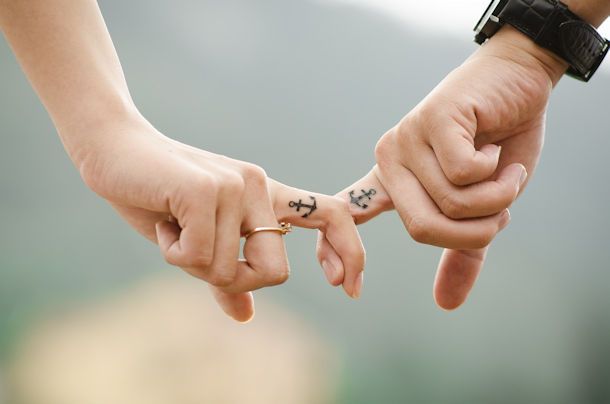
Migliori font per tatuaggi
Ci stavi pensando da tempo e adesso ti sei finalmente convinto a fare quel tatuaggio che desideravi tanto. Si tratta di una scritta, una frase o una parola che ti ricorda un momento speciale o rispecchia la tua personalità. Per questo hai deciso di metterti alla ricerca dei migliori font per tatuaggi, perché nulla va lasciato al caso. Deve essere tutto perfetto, carattere compreso: questo progetto ti sta particolarmente a cuore e vuoi ottenere il miglior risultato possibile.
Ti capisco, d'altronde il lato estetico di un tattoo non è affatto da sottovalutare. È giusto voler individuare lo stile di scrittura che meglio esprime il significato di ciò che stai per tatuare. E poi anche l'occhio vuole la sua parte, non è così? E allora nei prossimi paragrafi troverai tanti font tra cui scegliere, suddivisi per categoria, e non ci sarà soltanto il classico stile romano.
Non mi resta quindi che augurarti buona scelta, oltre a consigliarti di seguire le mie indicazioni per ottenere il font che preferisci o per spiegare al tuo tatuatore come realizzarlo. Sei pronto? Benissimo, anch'io lo sono: direi che possiamo iniziare a esplorare i numerosi caratteri che ho raccolto per il tuo prossimo tatuaggio. Buona lettura!
Come scegliere il font del tatuaggio
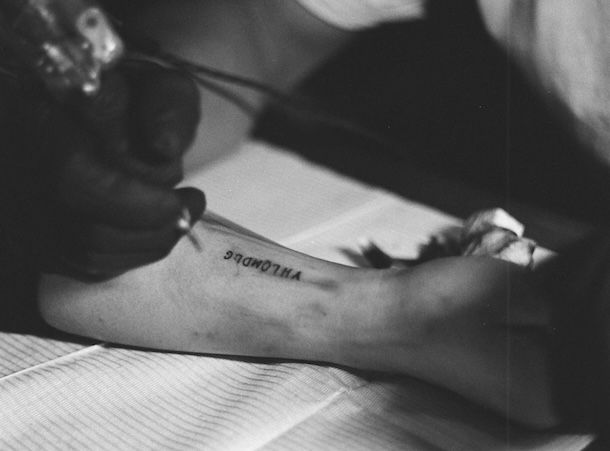
Il modo migliore per scegliere il font del tatuaggio è pensare al significato di ciò che stai per scrivere e all'effetto che desideri ottenere. Se, per esempio, vuoi trasmettere forza e decisione, potrebbe essere più adatto un carattere in stampatello maiuscolo, mentre se invece preferisci qualcosa di più elegante o romantico, i corsivi rappresentano spesso la soluzione ideale e ne esistono davvero di molto belli.
Nel caso in cui fossi totalmente indeciso, il mio consiglio per individuare i migliori font per tatuaggi è quello di selezionare diversi stili tra quelli che preferisci, installarli e provare a scrivere la parola o la frase del tattoo con ciascuno di essi. Guardando il risultato finale riuscirai più facilmente a capire quale tipologia di scrittura ti comunica le sensazioni che desideri evocare.
Tieni presente anche un altro aspetto importante: i caratteri troppo elaborati possono risultare difficili da leggere, soprattutto nei tatuaggi di piccole dimensioni. Per questo motivo è sempre bene trovare un giusto equilibrio tra estetica e leggibilità.
Migliori font per scritte tatuaggi
Veniamo ora al nocciolo della questione, come si suol dire, e andiamo a scoprire quali sono i migliori font per scritte tatuaggi. Nei capitoli che seguono trovi alcuni dei font a cui puoi attingere per realizzare il tuo tattoo, suddivisi per tipologia.
Font gotici
Scegliendo dei font gotici il tuo tatuaggio avrà uno stile antico, che richiama le lingue europee dei secoli passati. Ne ho raccolti qui di seguito alcuni che rappresentano diversi stili gotici, alcuni minuscoli e alcuni maiuscoli.
- Old London — il nome rende già l'idea di come sia questo font, è in grado di dare un carattere antico ea ricercato al tuo tatuaggio. Comprende numeri e caratteri speciali, ma anche lettere accentate.
- Enchanted Land — un carattere gotico, ma allo stesso tempo elegante, le lettere sono chiare e leggibili, dalla forma un po' arrotondata. Non manca nulla a questo font.
- Gothical — lettere sì, ma perché non anche qualche ornamento che renda il tatuaggio ancor più gotico? Scegliendo questo font, però, dovrai rinunciare a numeri, caratteri speciali e lettere accentate.
- Slaytanic — questo font è molto particolare, è gotico e dai tratti un po' metal. C'è bisogno del tatuaggio giusto per valorizzare questo carattere, ma purtroppo ci sono solo lettere maiuscole e lettere minuscole.
- Thunder Inferno — un font adatto ai tatuaggi metal, le lettere sono gotiche e al posto di alcuni caratteri speciali potrai incidere delle ali. Troverai tutte le indicazioni per ottenerle visitando la pagina del font.
- Celtic Garamond the 2nd — sì gotico, ma chiaramente leggibile e molto particolare, lo stile celtico è riconoscibile nell'immediato e sarà quel tocco in più per il tuo tatuaggio. Ci sono alcuni caratteri speciali, ma niente lettere accentate.
- Viking — se il mondo dei vichinghi è la tua passione, non potrai non avere un tatuaggio con questo font.
- God of War — rientra senza dubbio alcuno tra i font più belli per tatuaggi. Ha uno stile forte, deciso e bold. Le lettere sono grandi, imponenti e in grado di esprimere al meglio il concetto di forza che intendi esprimere con il tuo tattoo.